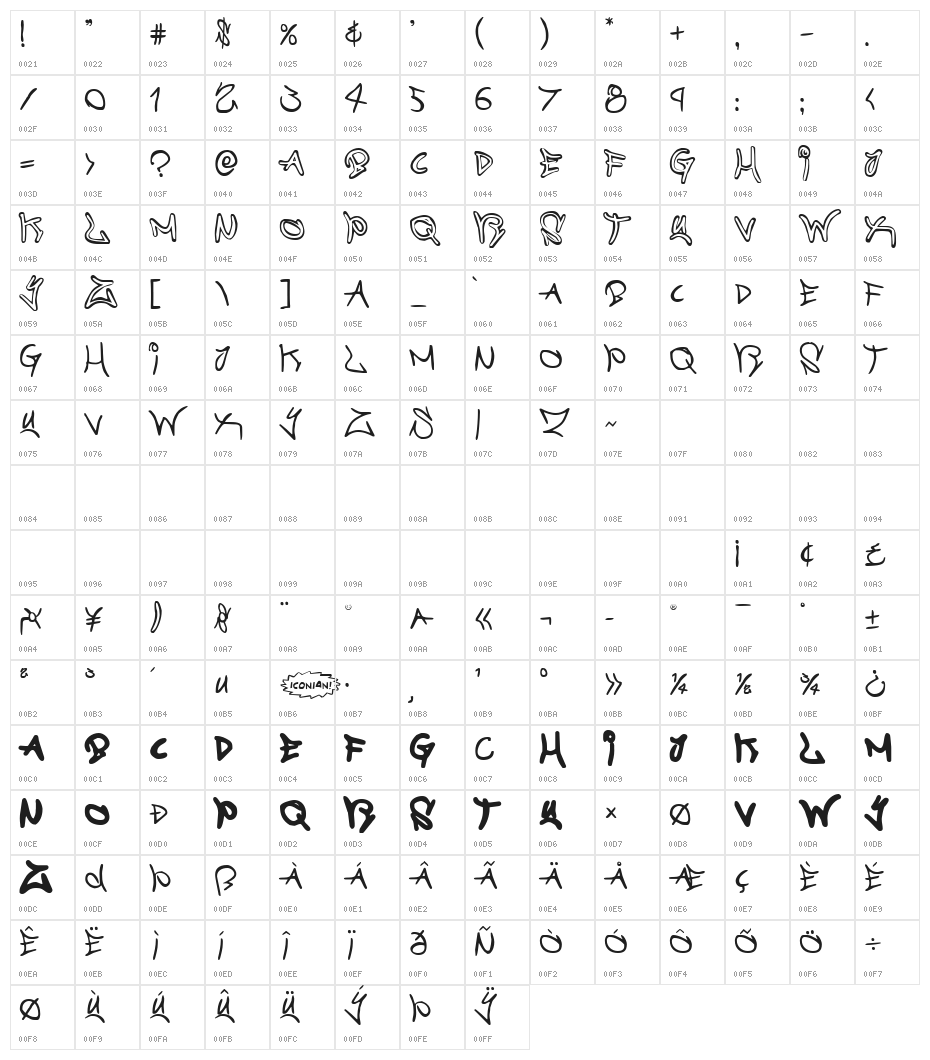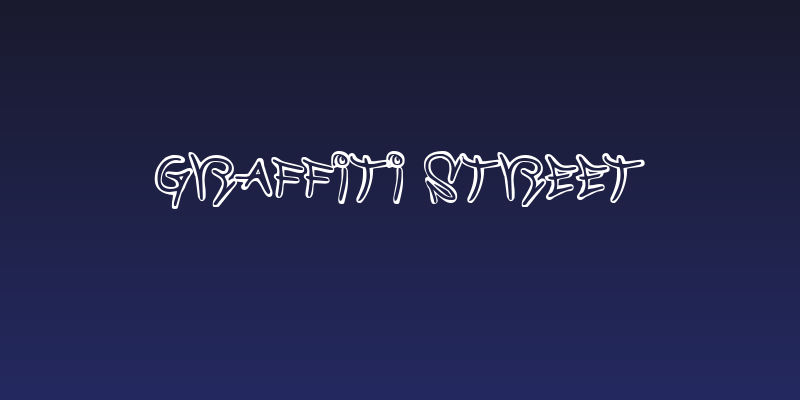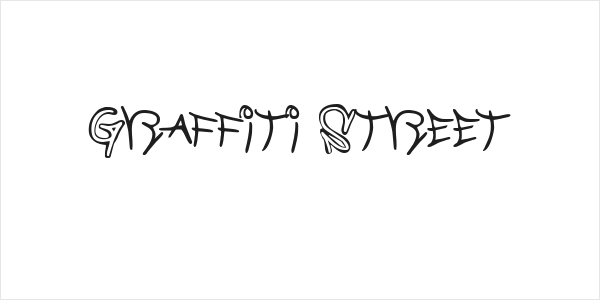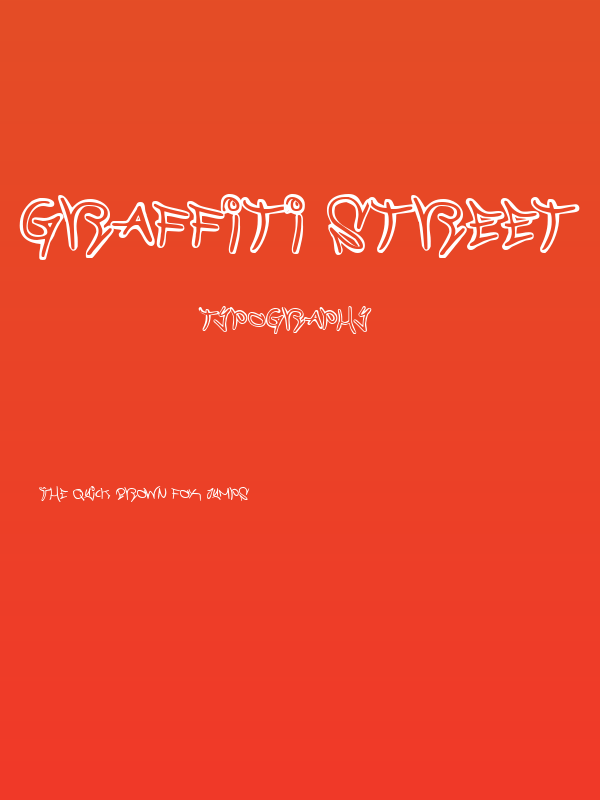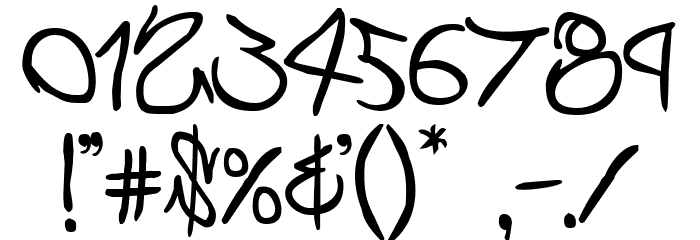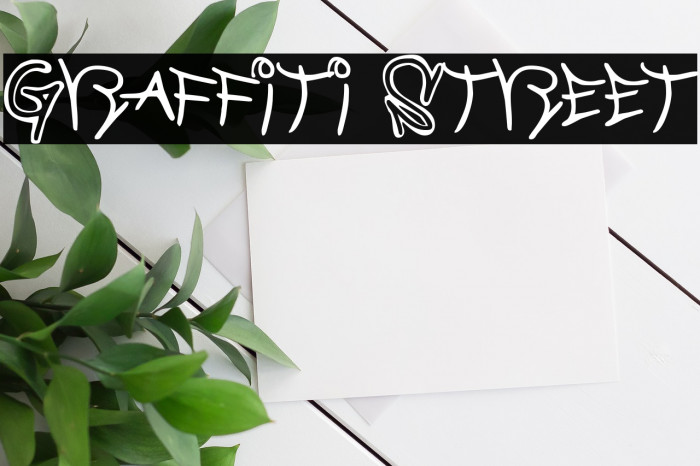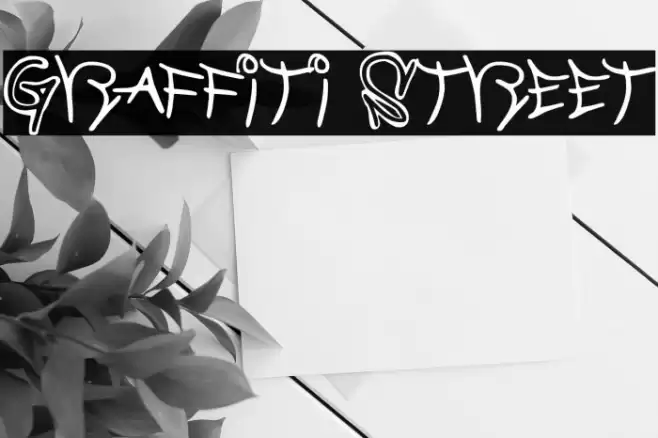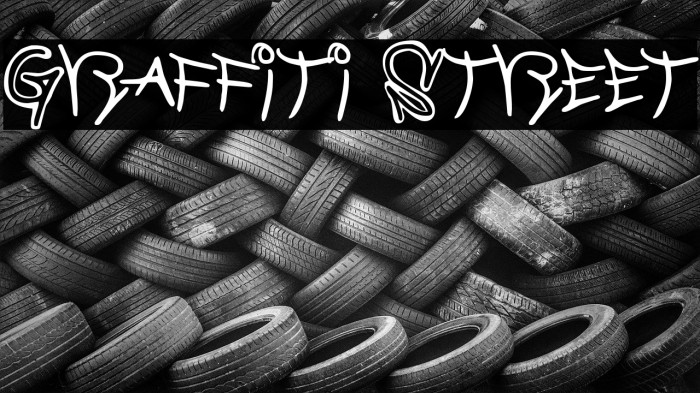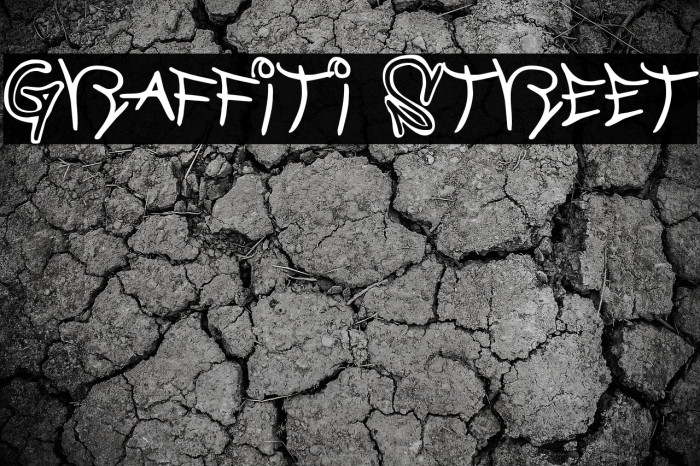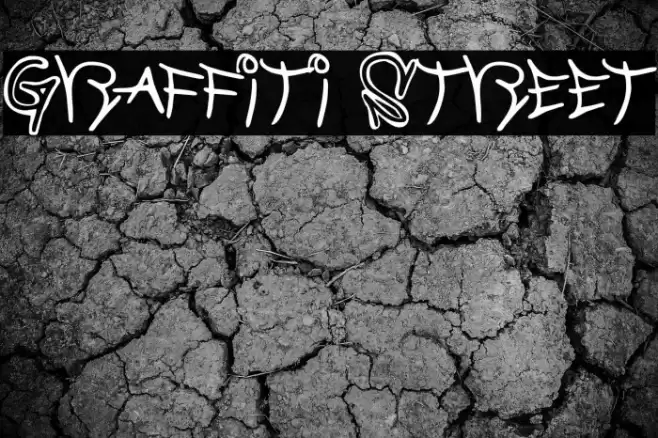
Graffiti Street Font
| カテゴリ | Graffiti |
| 全体的なスタイル | Urban, Artistic, Energetic |
| おすすめプロジェクト | Ideal for street art projects, urban-themed designs, music album covers, and event posters. |